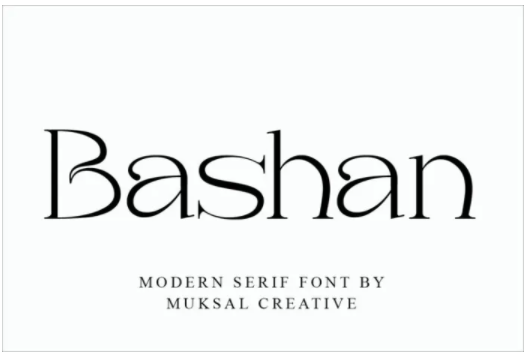
Fontbundles Bashan Font (2021)
Bashan - современный шрифт с засечками и красивым контрастом.
Специально разработан для проектов на модную тематику, прекрасно подходит для создания элегантных, шикарных, стильных дизайнов, таких как логотипы, заголовки, журналы и многое другое.